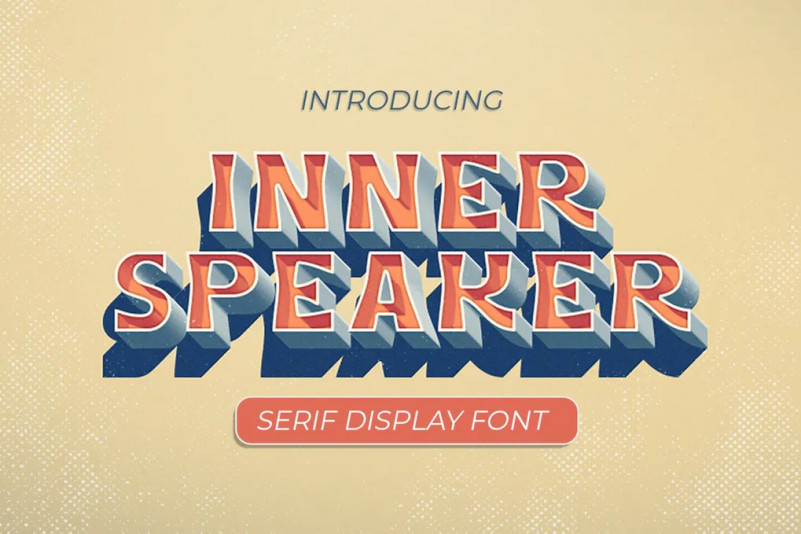
Innerspeaker Font
Une police Serif élégante, vintage et belle avec une touche élégante. La police Innerspeaker est parfaite pour les projets d’affichage tels que le texte cité, la carte postale, le Logo, la présentation, le thème de la nature, l’emballage de produits et bien plus encore. Il est également parfait pour le thème vintage et ancien – ou un texte élégant superposé à n’importe quelle image de fond.